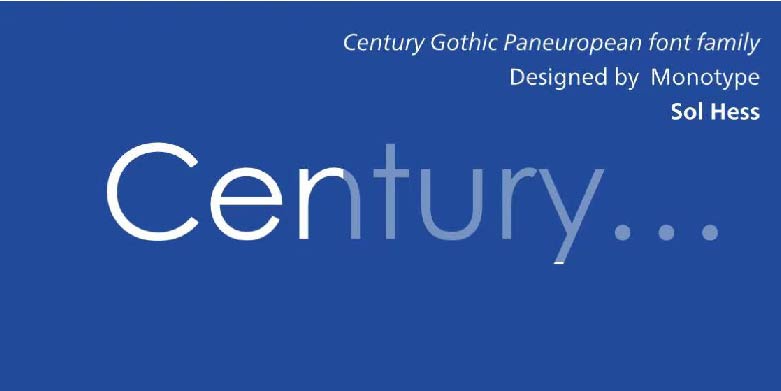
Century Gothic™
Century Gothic是Sol Hess于1936年至1947年间基于Monotype的Twentieth Century而绘制的。Century Gothic保留了Twentieth Century的基本设计,但增加了x字高并且为了确保其在现代数字系统中的显示让人满意而对其进行了修改。该设计受到20世纪20年代和30年代流行的几何风格无衬线字体的影响。Century Gothic字体家族适用于标题和一般的展示作品中,以及显示少量文本的情况,特别是在广告中。
Century Gothic is based on Monotype 20th Century, which was drawn by Sol Hess between 1936 and 1947. Century Gothic maintains the basic design of 20th Century but has an enlarged x-height and has been modified to ensure satisfactory output from modern digital systems. The design is influenced by the geometric style sans serif faces which were popular during the 1920s and 30s. The Century Gothic font family is useful for headlines and general display work and for small quantities of text, particularly in advertising.